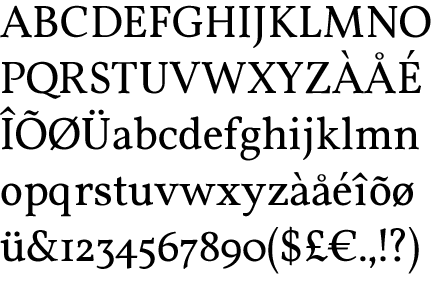
Zeitschriftenlayout – welche Schrift?
Für ein neues Zeitschriftenprojekt bin ich auf der Suche nach einer Schrift.
Kriterien:
- Serifen
- gut lebar (Zielpublikum zum Teil etwas älter)
- klassisch
Kann mir jemand weiterhelfen?
Bei den kostenlos erhältlichen ist die Auswahl wohl micht allzu groß:
Minion (liegt dem Adobe Reader bei):
Storms Lido:
Liberation Serif
Gentium Book Basic Beta (noch nicht 100%ig fertig, aber schon benutzbar):
Vollkorn (aber nur ein Schnitt):
Eventuell auch noch die Google-Droid-Fonts. Bei den preisgünstigen kommerziellen Schriften könnte die Leitura interessant sein: